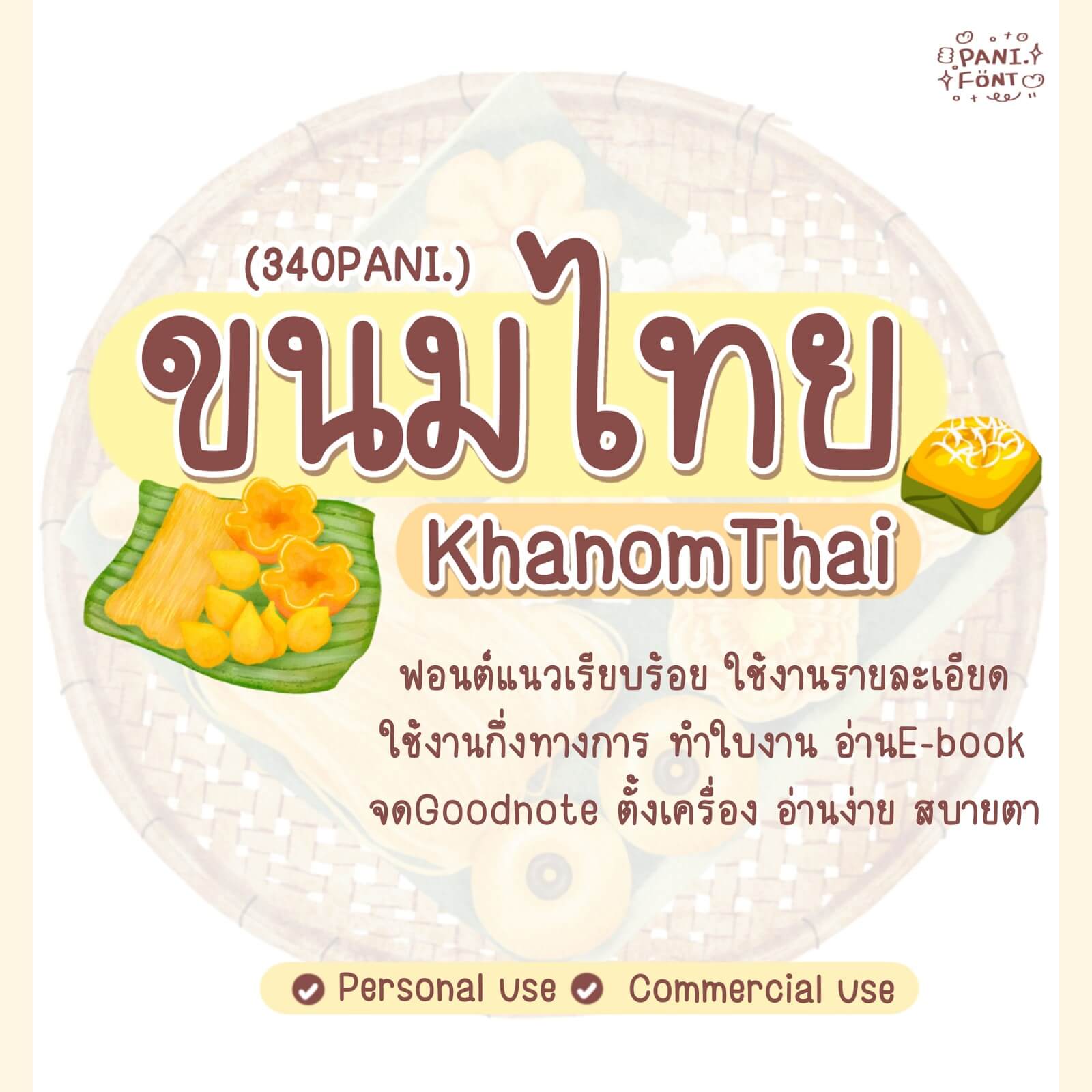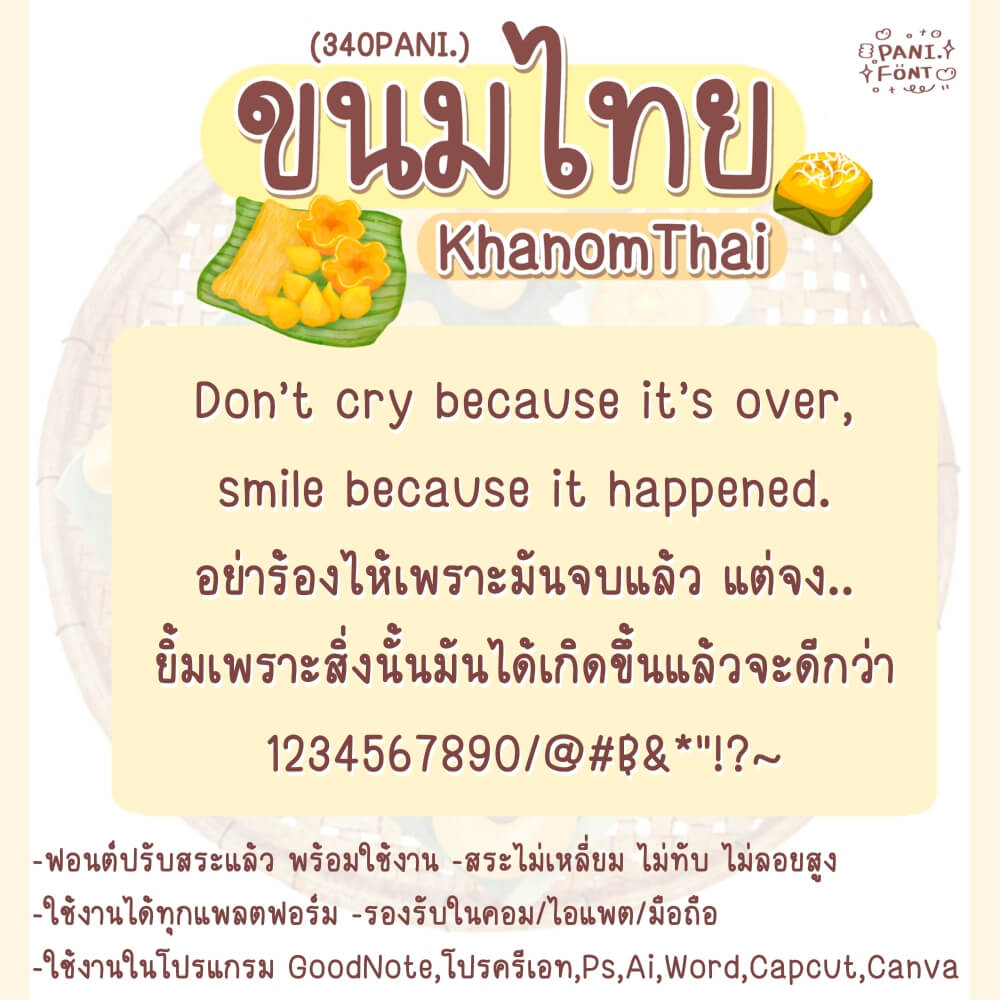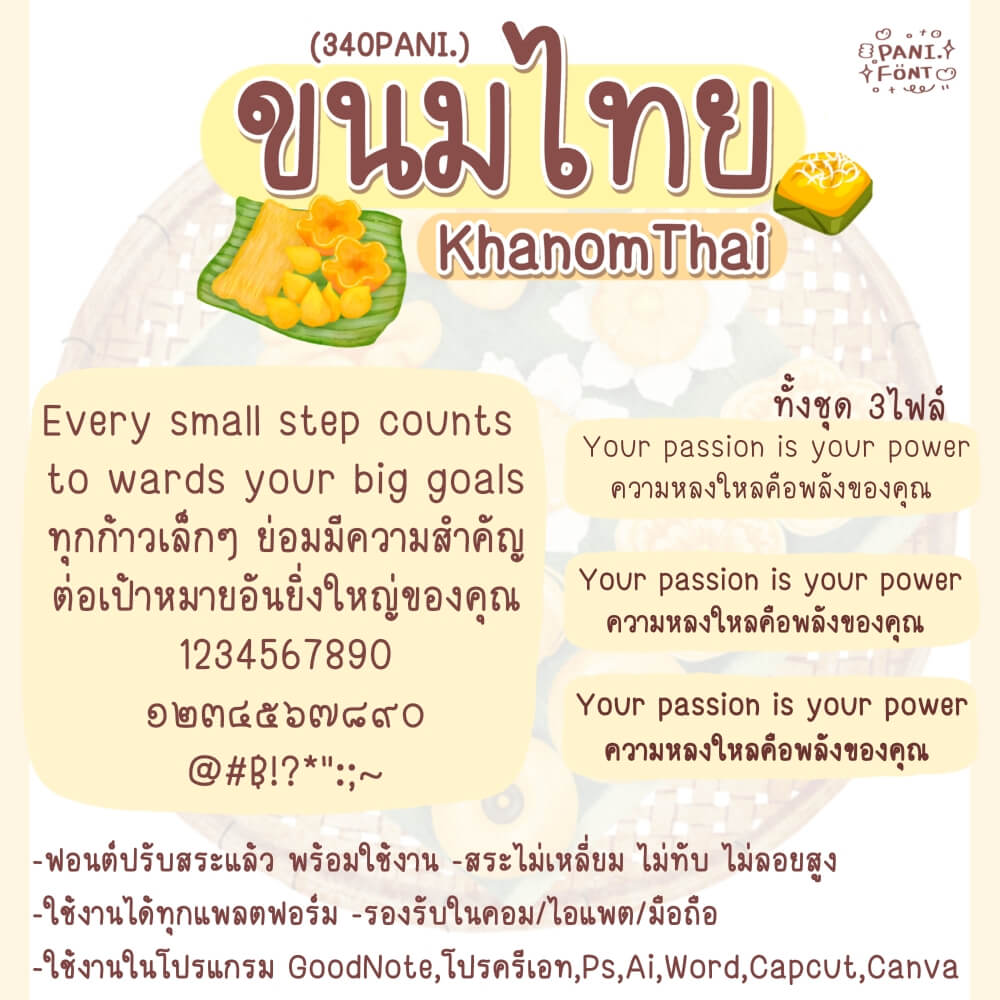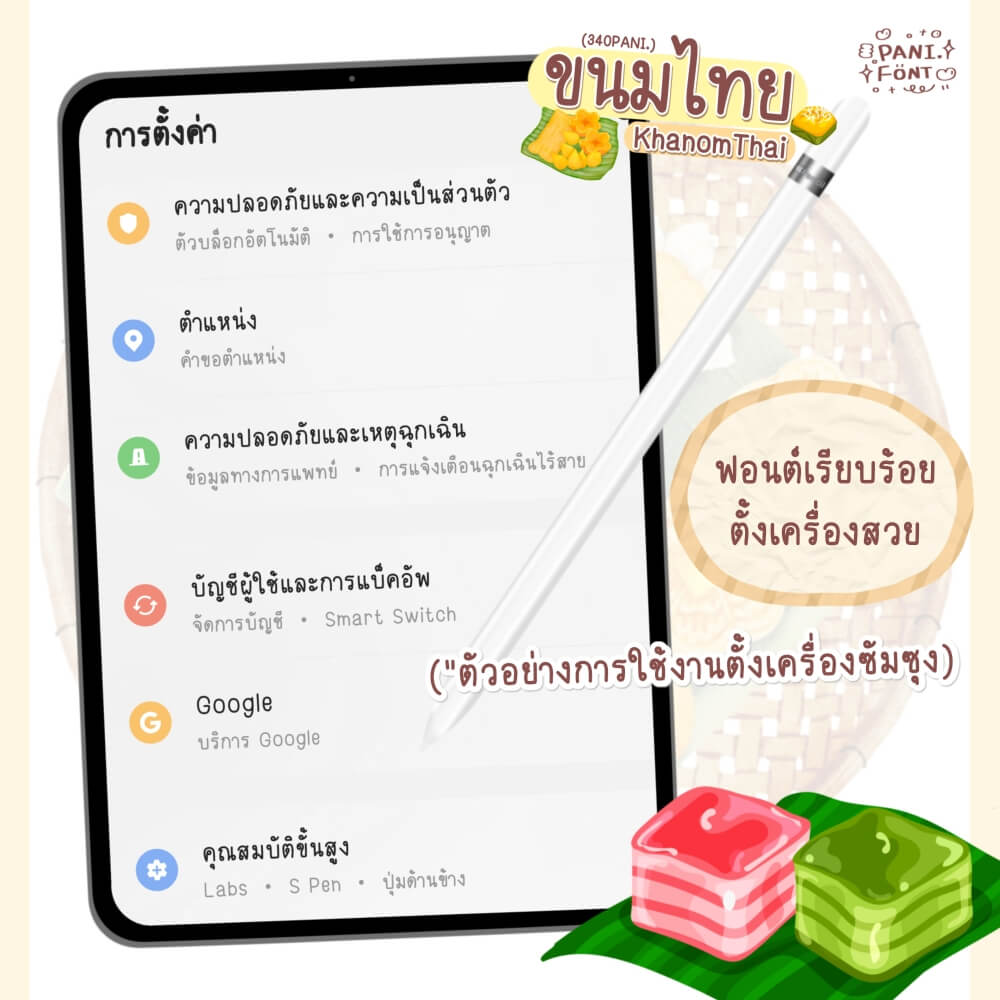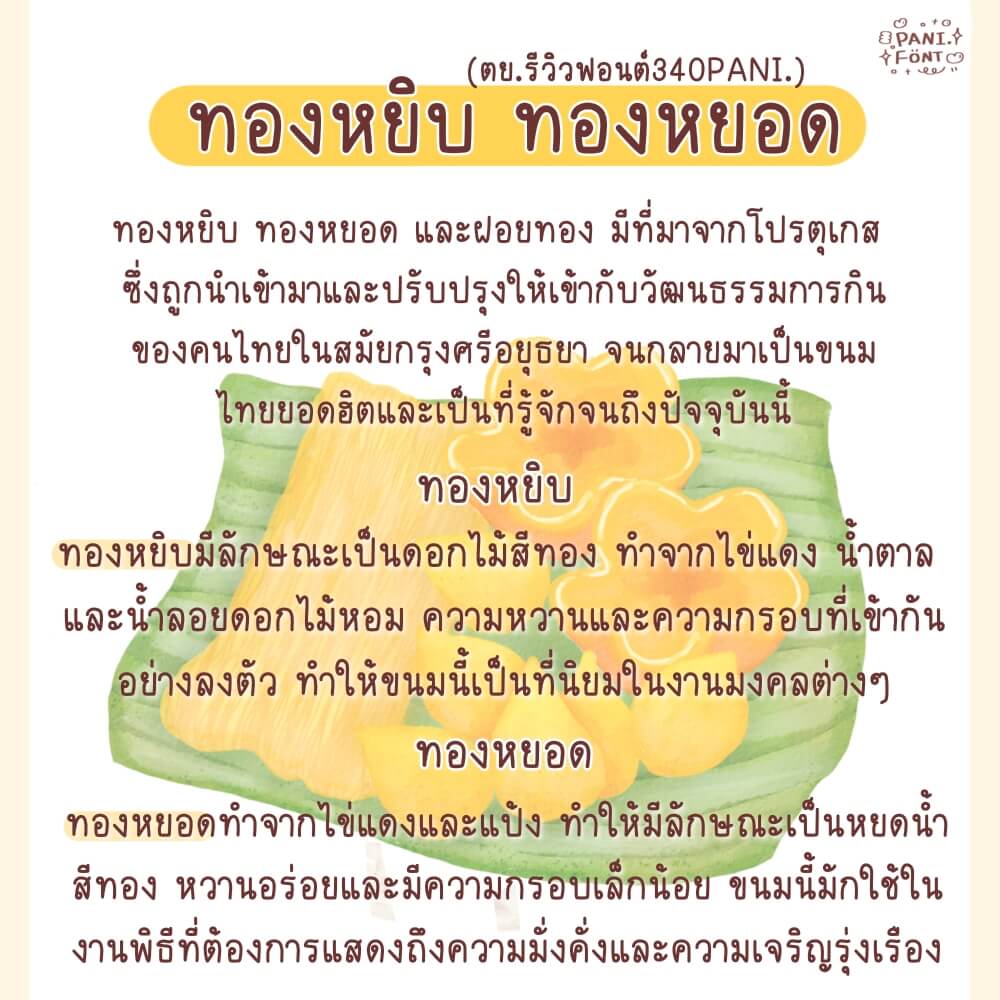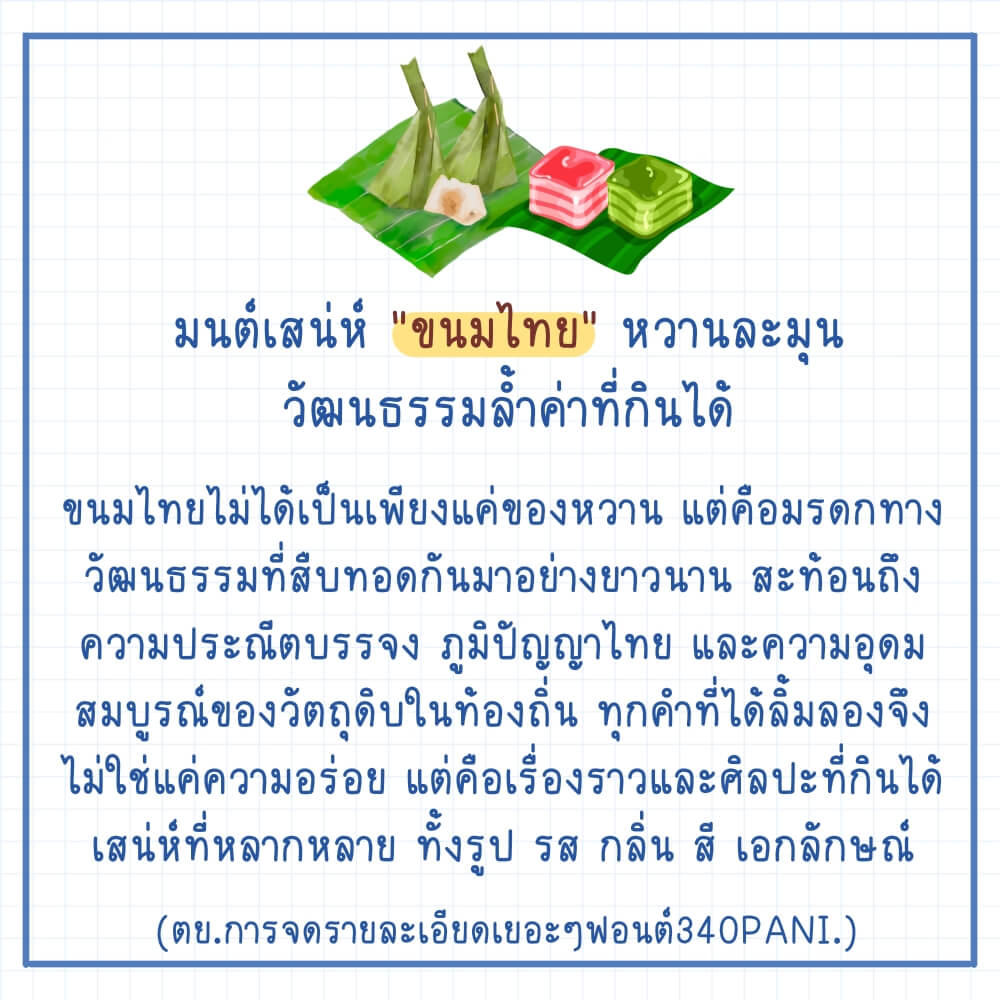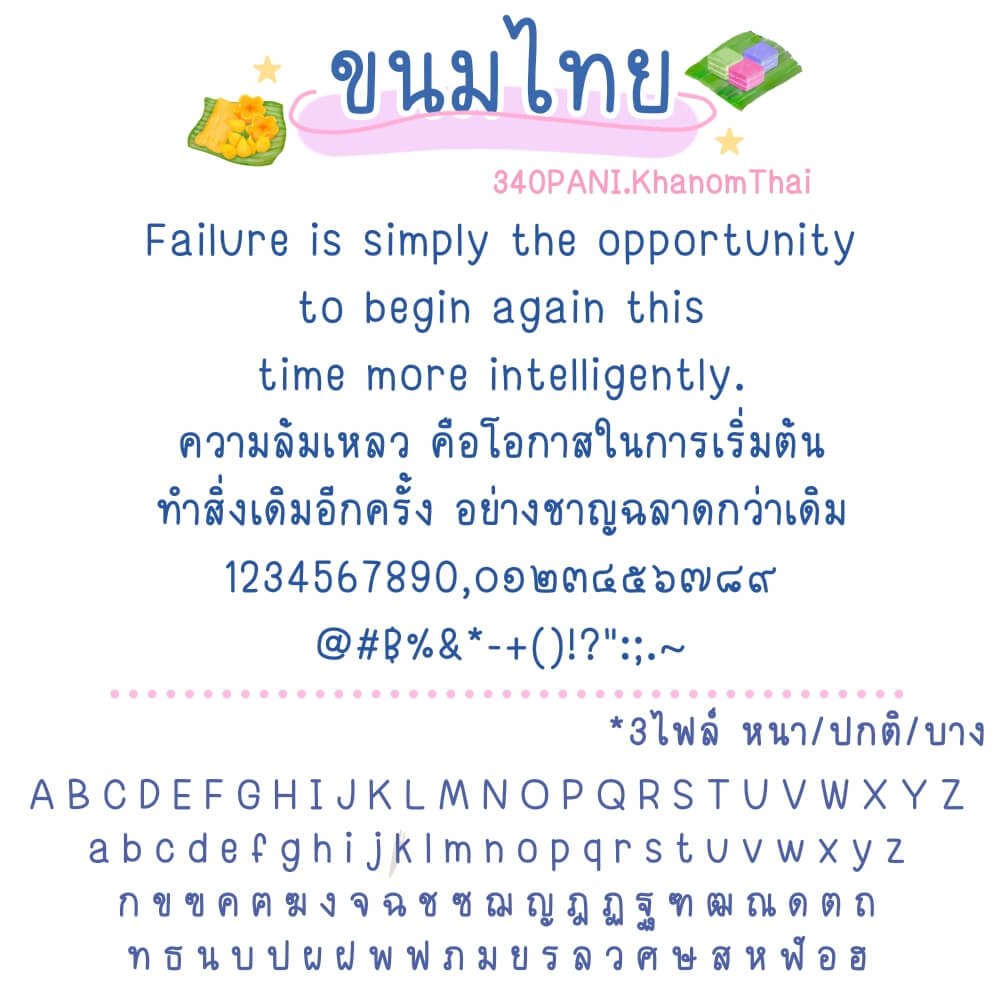
ฟอนต์ 340PANI.ขนมไทย – โหลดทดลองใช้ฟรีตัว Demo ฟอนต์แนวเรียบร้อย ใช้สำหรับแสดงรายละเอียด ใช้งานกึ่งทางการ ทำใบงาน อ่าน E-book จด Goodnote ตั้งเป็นฟอนต์เครื่อง อ่านง่าย สบายตา *แนะนำ สำหรับสายเรียบร้อยค่ะ*
340PANI.ขนมไทย